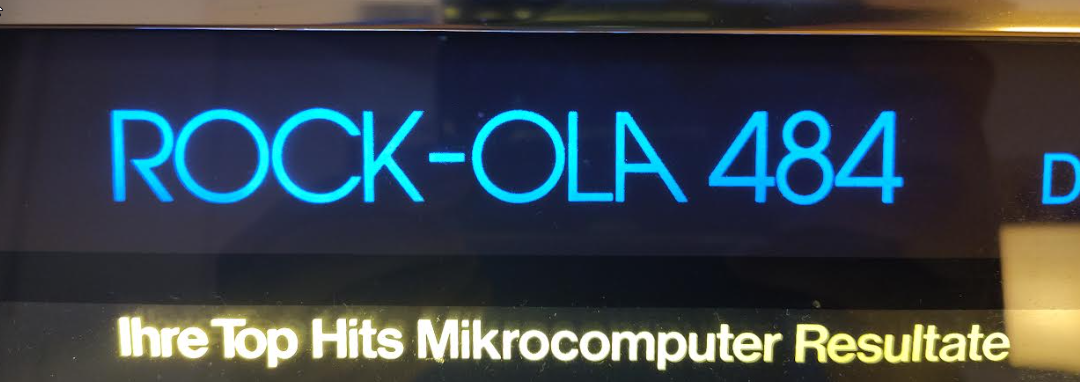
Welche Schriftart hat dieser Jukebox Tag "Rock-Ola 484"?
ich benötige bitte Informationen zu dieser Schriftart.
Es ist die Bezeichnung einer US Jukebox aus den späten 80er Jahren.
Das ist die Avant Garde Gothic.
Meinst Du das schräge A ist selbst erzeugt, oder sind solche Buchstaben kombinierte Schriftarten?
Auf der Herstellerseite gibt es mehrere Beispiele, wo Buchstaben "verschoben/aneinander" gesetzt sind.